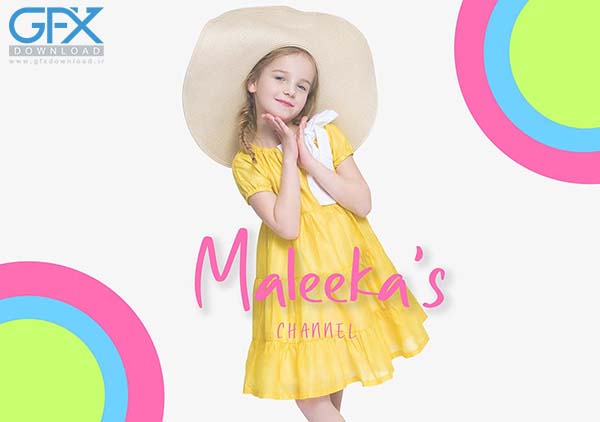
دانلود فونت رایگان Patrick
فونت کودکانه پاتریک
فونت پاتریک یک قلم نمایش زیبا و شگفت انگیز با مضمون کودکانه می باشد که می توانید در سایر پروژه ها از این فونت رایگان استفاده نمایید.فونت پاتریک در 3 فرمت مختلف OTF/TTF/WOFF عرضه شده و حجم دانلود آن بسیار پایین می باشد.فونت پاتریک Patrick مناسب برای برندسازی پروژه ها ، آرم ، طراحی جلد کتاب ، طرح های تی شرت ، پست رسانه های اجتماعی ، تبلیغات ، بسته بندی محصول ، طرح های محصول ، برچسب ، علامت چاپی ، دعوت نامه ، لوازم التحریر و هر پروژه دیگری است.در ادامه مطلب با دانلود فونت رایگان Patrick همراه جی اف ایکس دانلود شوید...